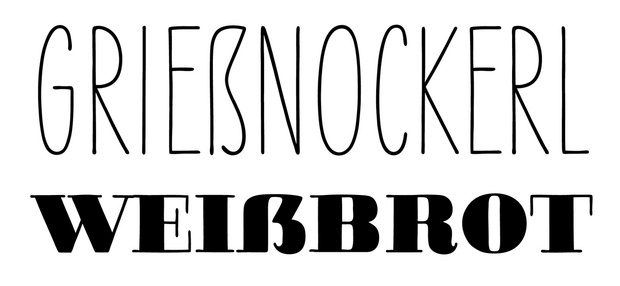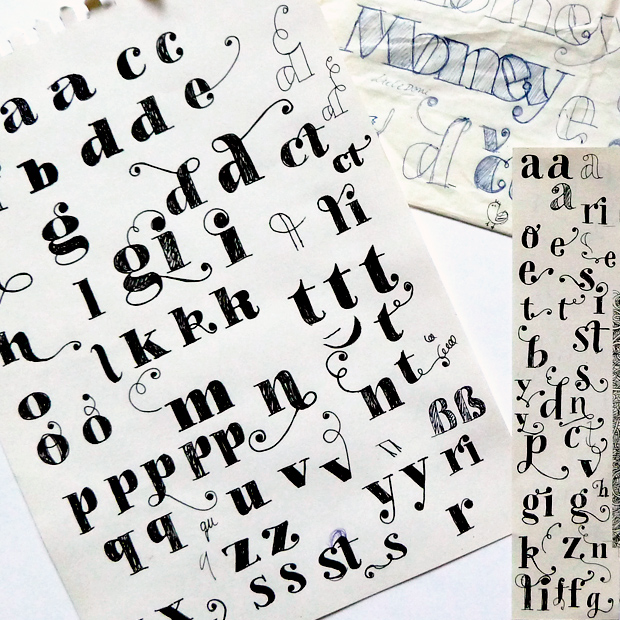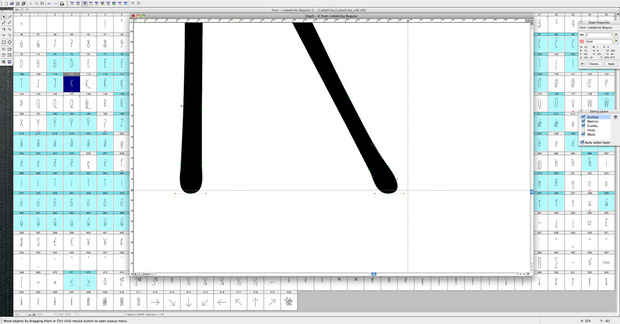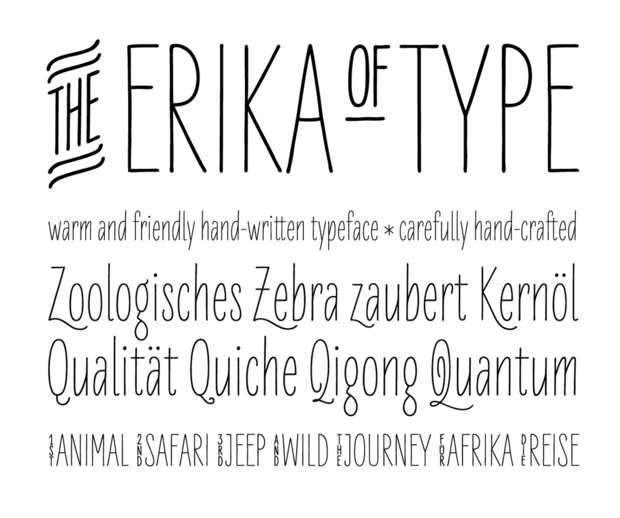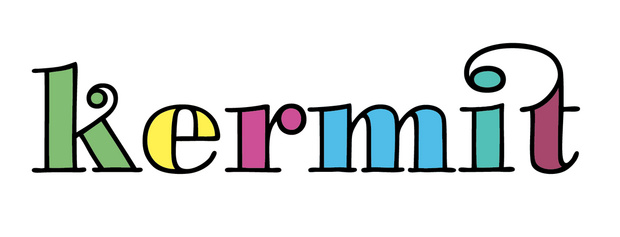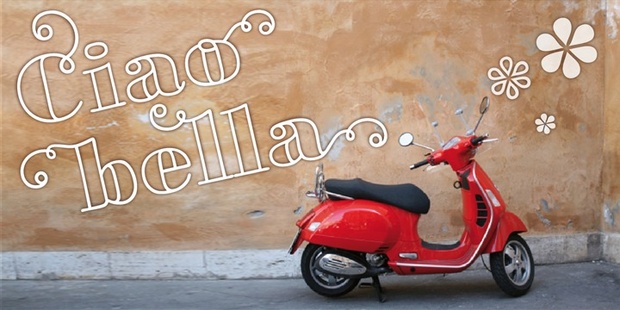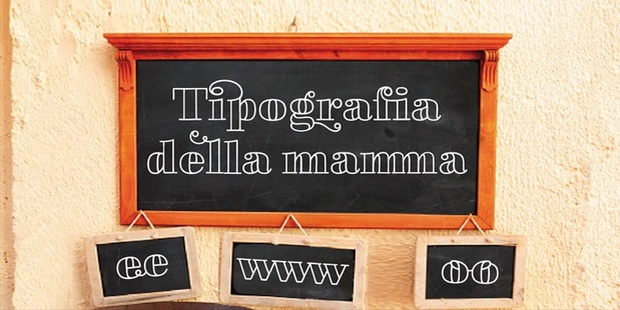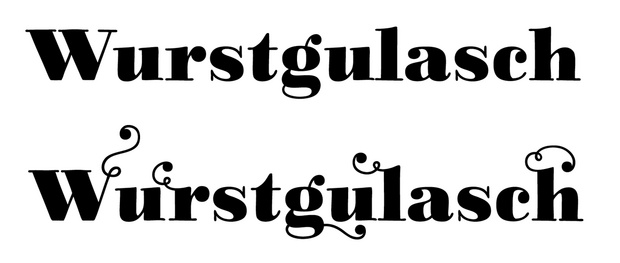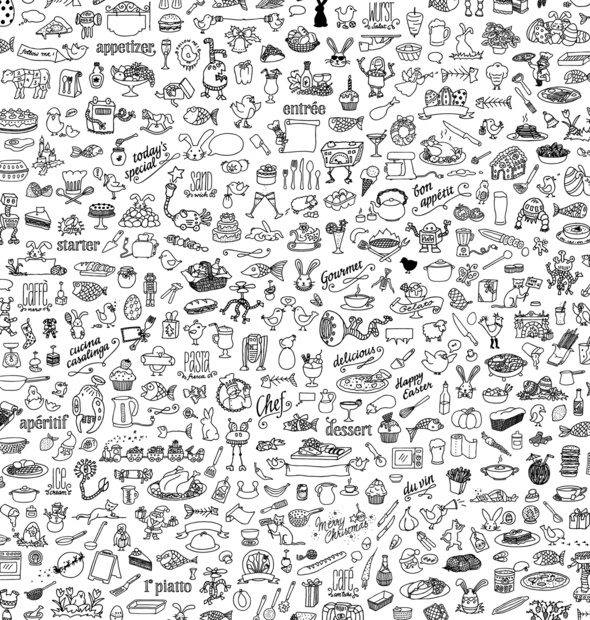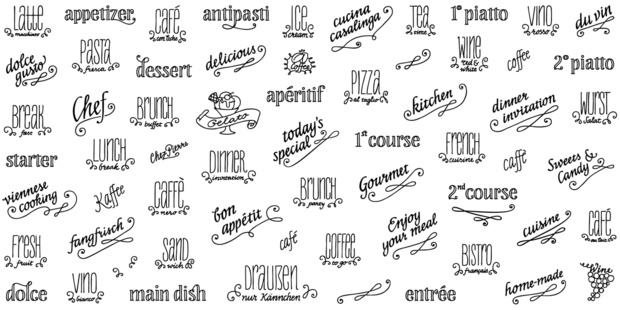
Interview mit LiebeFonts
Ulrike Wilhelm aus Berlin verbindet Schrift und Illustration auf höchst interessante Weise und der Erfolg gibt ihr Recht. Ihre erste vollständige Schrift, die LiebeErika, wurde unter die besten MyFonts-Schriftveröffentlichungen des Jahres 2010 gewählt. Im nachfolgenden Interview verrät Ulrike etwas mehr über ihre Schriften und ihre Arbeitsweise.
Wie bist Du zum Typedesign gekommen?
ccs-1-1357467448,7814.pngEigentlich eher nebenbei. Ich habe zwar im Studium an der FH Potsdam zwei, drei Mal den Schriftgestaltungskurs von Luc(as) de Groot besucht. Aber eigentlich haben mich spontane, analoge Arbeitsweisen wie Illustration und Kalligrafie immer mehr interessiert als das stundenlange Optimieren von Bézierkurven. Im Abschlussprojekt meines Kommunikationsdesign-Studiums habe ich sogar versucht, eine universelle Schrift ohne Buchstaben – nur mit Piktogrammen – zu gestalten. Das hat natürlich nicht so richtig geklappt und ist sowieso mit einem Augenzwinkern zu verstehen. Aus diesen piktogrammartigen, handgezeichneten Illustrationen ist dann auch die Idee entstanden, die Illustrationen in eine Fontdatei zu pressen und bei MyFonts zu verkaufen. Das hat Spaß gemacht und wurde auch ganz gut angenommen, deshalb kamen immer mehr Piktogrammfonts dazu. Irgendwann habe ich dann gemerkt, dass es keine Schrift gab, die hundertprozentig zu meinen Illustrationen und Piktogrammen passte. Deshalb habe ich mich letztes Jahr an meine erste »richtige« Schrift gewagt: LiebeErika.
Zeichnest Du per Hand am Computer oder zuerst auf Papier?
Unterschiedlich. Es fängt aber immer analog an. Die ersten Skizzen landen immer auf Papier. Ich arbeite auch gerne mit meinem Zeichentablett in Photoshop, weil ich da sauberer und präziser arbeiten kann als mit gescannten Zeichnungen. Den Schritt zur Vektorgrafik mache ich erst, wenn die wichtigsten formalen Entscheidungen getroffen sind. Ich versuche auch, nicht zu viel Vektorkosmetik zu betreiben. Schließlich leben meine Fonts von den handgemachten Unregelmäßigkeiten. Manchmal mache ich auch nachträglich Abschlüsse noch etwas dicker oder Striche etwas wackeliger, um einen unregelmäßigen Tintenfluß zu simulieren.
In LiebeErika und LiebeDoni gibt es etliche kontextabhängige Alternativformen, so dass zwei aufeinanderfolgende identische Buchstaben nicht genau gleich aussehen. Das hilft in meinen Augen sehr, das »Handgemachte« glaubwürdiger rüberzubringen.
Was hat es mit der »Liebe« im Namen Deiner Fonts auf sich?
Wie ich genau darauf kam, weiß ich gar nicht mehr. Ich finde aber, dass der Name ganz gut zu den liebevoll gezeichneten und irgendwie lieb aussehenden Fonts passt. Es ist auch ziemlich praktisch: Wenn ich eine neue Schrift mache, ist die Hälfte des Namens schon fertig. Mir war es auch wichtig, dass meine Marke ein Stück Herkunft kommuniziert, deshalb kam ein komplett englischer Name nicht in Frage. Und der Name funktioniert international erstaunlich gut.
LiebeDoni – die eigentlich so strenge Bodoni mit handgezeichneter Charakter umgesetzt. Wie kamst Du auf diese Idee?
Ich mochte Bodoni schon immer gerne, besonders in fett und groß. Deshalb hatte ich auch in meinem Font LiebeMenuLettering einige Wörter in einer Art Bodoni gezeichnet. Daraufhin habe ich viele Anfragen bekommen, ob es denn die Buchstaben auch einzeln gebe. LiebeDoni ist auch ein schöner Kontrast zu LiebeErika: Die eine fett, breit und mit Serifen, die andere filigran, schmal und serifenlos.
Schriften wie Deine LiebeDoni haben einen umfangreichen Zeichenausbau. Wie lange dauert die Entwicklung Deiner Schriften von den ersten Skizzen bis zum verkäuflichen OpenType-Font?
Die »richtigen« Schriften sind wesentlich aufwendiger als die Piktogramm-Fonts. An LiebeDoni habe ich alles in allem ungefähr ein halbes Jahr gearbeitet, allerdings nicht Vollzeit. LiebeErika ging etwas schneller, vermutlich weil man bei der geringen Strichstärke und dem fehlenden Kontrast schneller zu harmonischen Wortbildern kommt. Wahrscheinlich würde alles schneller gehen, wenn ich mich nicht so im Detail verlieren würde. Aber ich kann es nicht lassen, mir immer wieder doch noch eine weitere lustige Ligatur oder Alternativformen auszudenken. Ich bin auch sehr geduldig und diszipliniert. Ich glaube, das ist wichtig, wenn man Schriften gestalten will.
Du vertreibst Deine Schrift selbst über MyFonts und bist also neben dem Entwurf auch für das technische Mastering, Marketing, Kundenbetreuung und so weiter zuständig. Betrachtet du diese Arbeitsweise eher als Fluch oder Segen? Wie organisierst Du Deine Arbeit um Dich nicht in diesen vielen Arbeitsbereichen zu verzetteln?
Ich genieße die Freiheit, alles selbst machen zu können. Ich freue mich bei jedem Arbeitsschritt schon auf den nächsten. Ich mache mir beim Zeichnen der Buchstaben immer schon Gedanken darüber, wie die Anwendungsbeispiele aussehen könnten. Und wenn ich später beim Gestalten der Marketing-Materialien noch Probleme finde, kann ich einen Schritt zurückgehen und einzelne Buchstaben noch im Detail korrigieren.
Ich habe außerdem jemanden zu Hause, der von dem Thema Ahnung hat, jede Zeichnung kritisch betrachtet und auch ein gutes Gespür fürs Marketing hat. Und einige Tester im Freundeskreis werden mit Betaversionen versorgt, so dass ich schon vor der Veröffentlichung wertvolles Feedback bekomme.
Hast Du Vorbilder im Bereich Schrift oder Illustration?
Die Schule von Luc(as) de Groot hinterlässt wohl bei jedem seiner Studenten sichtbare Spuren. Hohe Ansprüche an die Lesbarkeit und gewisse humanistische Konstruktion sind dann einfach so drin, dass man gar nicht mehr darüber nachdenkt. Ich schaue mir auch sehr gerne die Arbeiten von Jessica Hische und Seb Lester an.
Welche Font-Projekte können wir in Zukunft von Dir erwarten? Weitere Ornamente, Schriften oder etwas ganz anderes?
Momentan arbeite ich intensiv an einem noch geheimen Projekt. Es ist eine Art Touchscreen-Kinderbuch, so viel kann ich verraten. Parallel entwerfe ich auch schon die nächste Schrift, die wieder in eine andere Richtung geht als die ersten beiden: eine geschriebene, verbundene Schwungschrift.